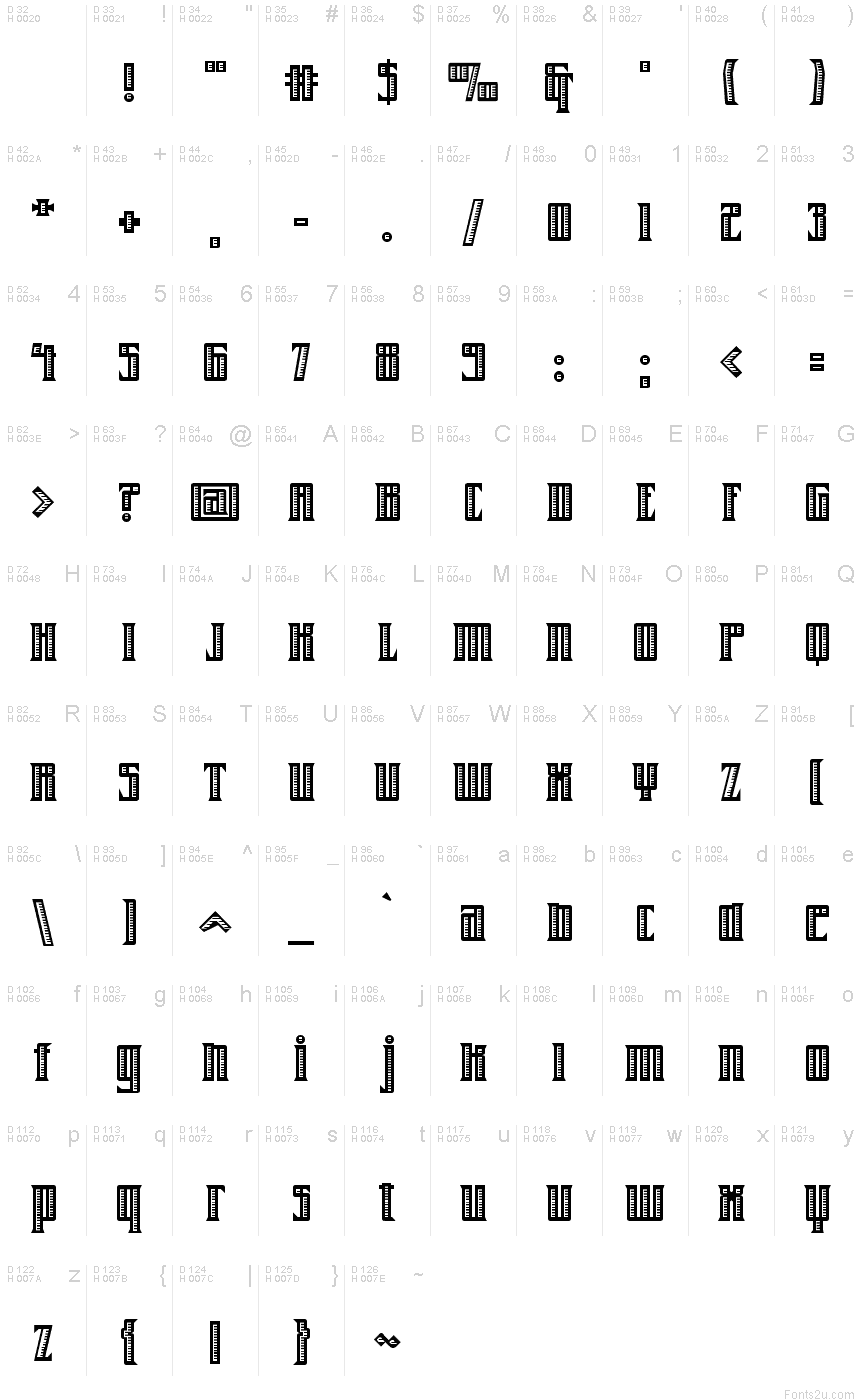
Farrier ICG Shaded od Image Club Graphics to darmowy, utrzymany w stylu retro krój typu display o wyrazistych, prążkowanych kształtach, które przywodzą na myśl stare szyldy jarmarczne i plakaty cyrkowe. Wysokie, kanciaste litery wypełnione drabinkowym cieniowaniem i drobnymi, ząbkowanymi krawędziami nadają im niemal namacalną fakturę, przypominającą nadruk na drewnie. Efekt jest mocny, graficzny i cudownie nostalgiczny – jak litery zdjęte prosto ze starego afisza.
Dzięki Farrier ICG Shaded Twój tekst natychmiast stanie się punktem centralnym projektu. To naturalny wybór na plakaty imprezowe, zaproszenia na imprezy tematyczne, retro logotypy, szyldy, okładki albumów czy wyróżniające się opakowania. Wewnętrzne prążkowanie dodaje wbudowanego rytmu, dzięki czemu krótkie słowa i składane linie są czytelne nawet z odległości. Ten darmowy font świetnie komponuje się z prostym, geometrycznym krojem bezszeryfowym – pozwól, by Farrier ICG Shaded przejął duże, przyciągające wzrok hasła, podczas gdy bezszeryfowy font zajmie się resztą detali.